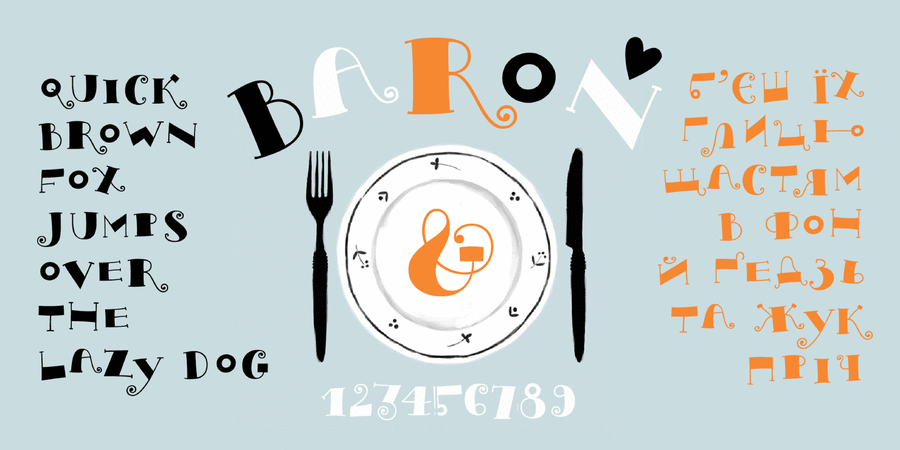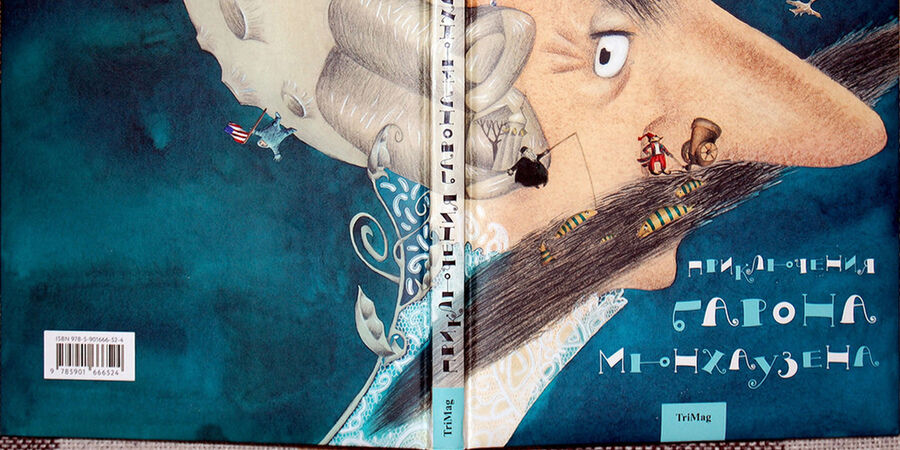
Шрифт Барон – це вдосконалена версія шрифту Акатік, створеного для заголовків у книжці про барона Мюнхаузена. Книгу надруковано у видавництві ТриМаг. Шрифт отримав диплом 3 ступеня за досконалість у шрифтовому і графічному дизайні на конкурсі студентських шрифтових робіт, організованому фірмою ParaType. В оновленій версії до наявної кирилиці додана базова латинка та значно покращені цифри. Шрифт розробила Світлана Акатьєва за участю Олександри Королькової, латинку та цифри для нової версії розробила Марчела Можина у 2019-2020 році.
Асоціації з сімейством шрифтів Baron TypeОсобистість і характер гарнітури:
казковий, дитячий, наївний, чарівний, милий, артистичний, весняний, літній, святковий, свіжий, добрий, зелений, музичний, ритмічний, сентиментальний, художній, чуттєвий, лихий, неформальний, грайливий, веселий, непосидючий, емоційний, радісний, неслухняний, пустотливий, рухливий, цікавий, оригінальний, вільний, задерикуватий, енергійний, характерний, привітний, живий, дівчачий, мультяшний, смачний, рукотворний, прикольний, кучерявий, доброзичливий, добродушний, вигадливий, смішний, самобутній, неординарний, мажорний, інфантильний, легковажний, повітряний, дурний, безглуздий, вітряний, крихкий, небувалий, хитрий, сміливий, динамічний, стрибучий, танцюючий, дивний, домашній, усміхнений, щасливий, творчий, гарненький, симпатичний, екзотичний
розваги, квіти, іграшка, завивка, брошка, біжутерія, прикраса, аксесуари, перукарня, хенд мейд, сувенір, дитячий ранок, сад, клумба, щоденник, принцеса, казка, собачка, болонка, гра, зоопарк, зоомагазин, тварини, відпочинок, табір, весна, свято, подарунки, магія, цукерки, солодощі, десерт, кондитер, музика, торт, літо, канцтовари, дитяча книжка, пригоди, анімація, мультфільм, день народження, сукня, одяг, базар, дитсадок, канікули, школа, гумор, Хюґе, графіка, ілюстрація, школярка, дім, малюк Гарнітура має ознаки стилів: